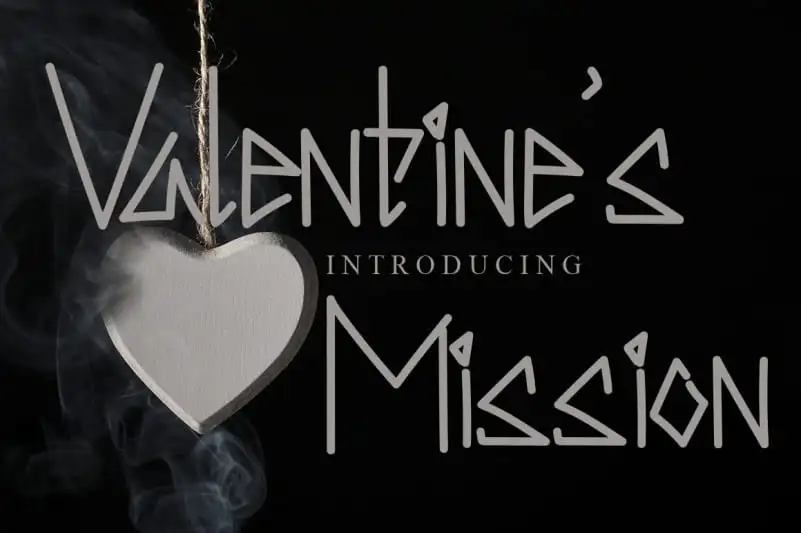
Valentine’s Mission Display Font – Fonte Grátis
Valentine's Mission Display Font
A fonte Valentine’s Mission Display Font é uma escolha perfeita para quem busca um touch moderno em seus projetos. Ela se destaca com sua estética cool e atual, combinando elegância com criatividade. Seja você que está fazendo crafts pessoais ou trabalhos de design digital, entregando presentes personalizados, ou mesmo criando cartas de aniversário, esta fonte atende todos esses requisitos. Com seu formato Display, Valentine’s Mission Display Font transforma qualquer projeto em algo realmente único e chamativo. Ideal tanto para uso pessoal como profissional, ela é um elemento que certamente fará sua marca. Alem disso, a proposta de designer LevinCreative traz uma dose extra de criatividade, garantindo que você encontre sua própria maneira única de expressar-se através da fonte.